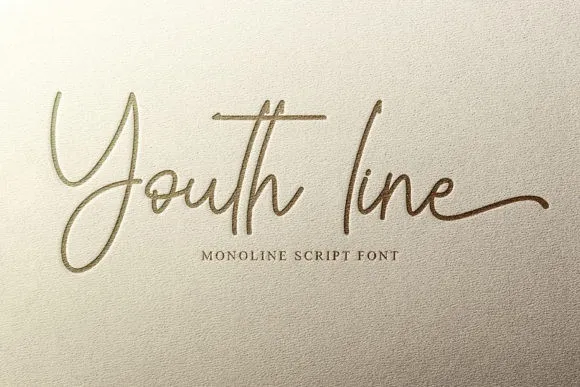
Youth line Font – Download Grátis
Esta é uma nova e linda tipografia feita à mão com traços monolineares, espaçamento compacto e personagens divertidos. Ela transmite delicadeza e alegria, tornando-a perfeita para escrita de convites de casamentos, cartas ou qualquer design que possa precisar de um toque romântico e personalizado. Perfeito para designers e tipógrafos que buscam uma abordagem fresca e divertida ao trabalhar com textos em projetos de alto padrão.